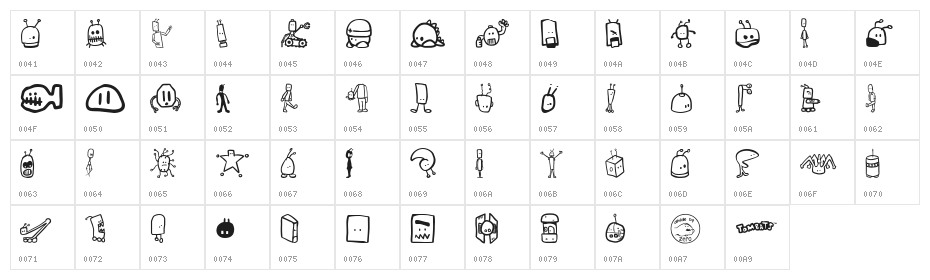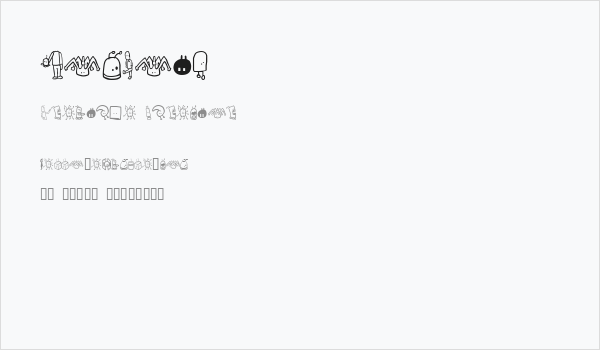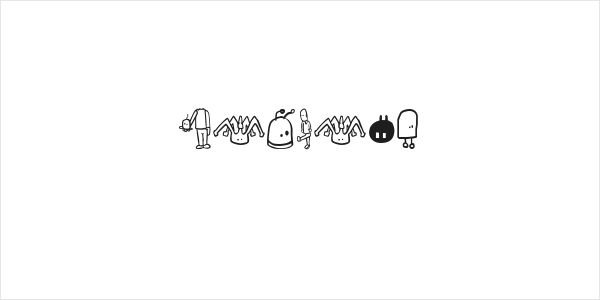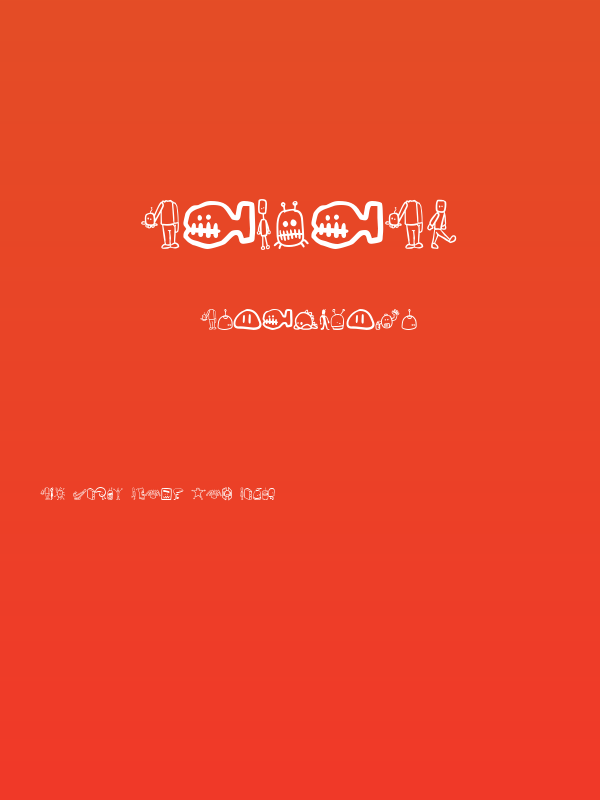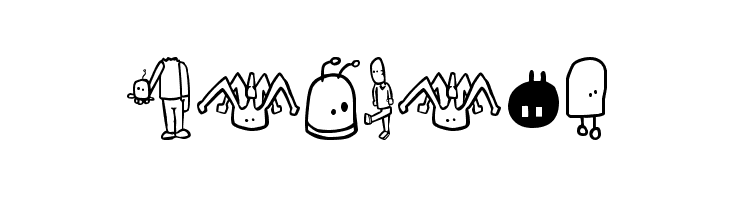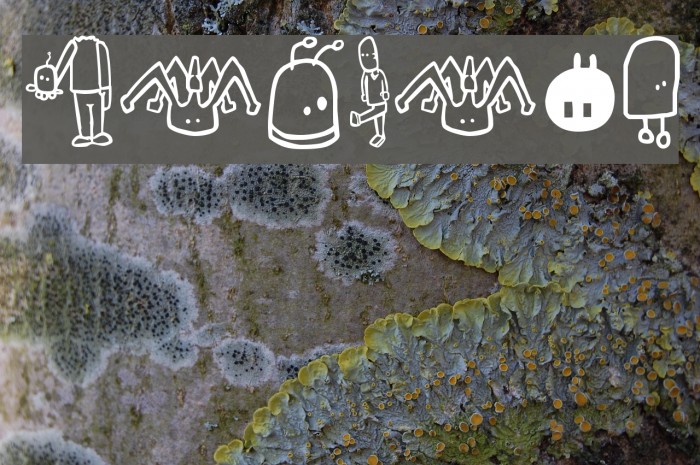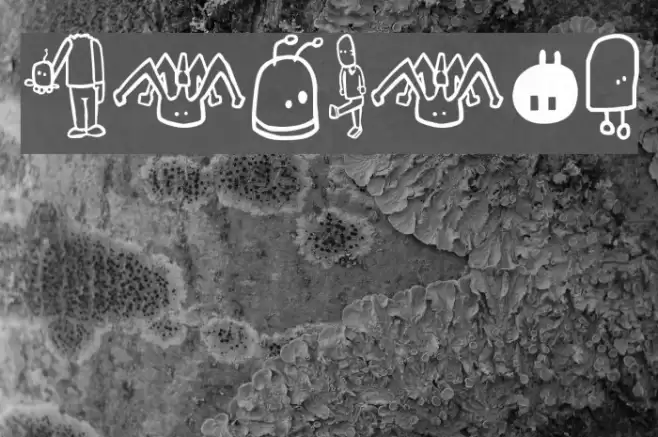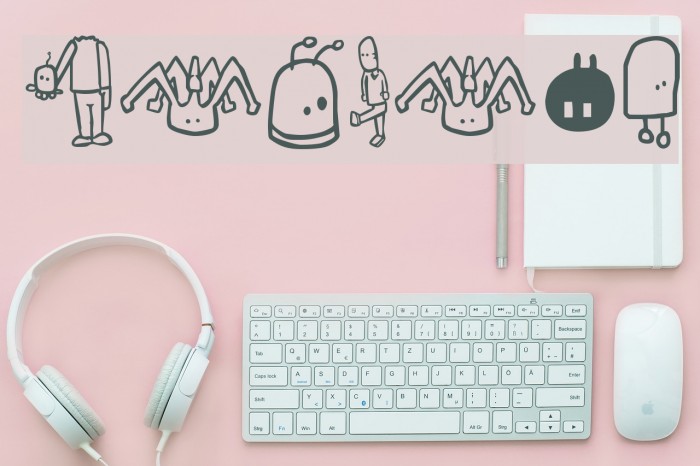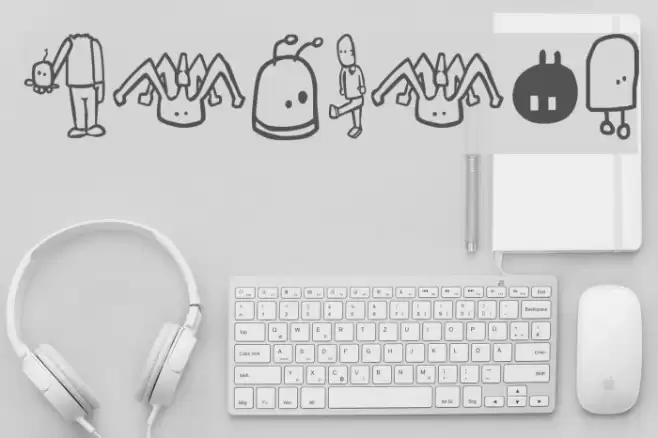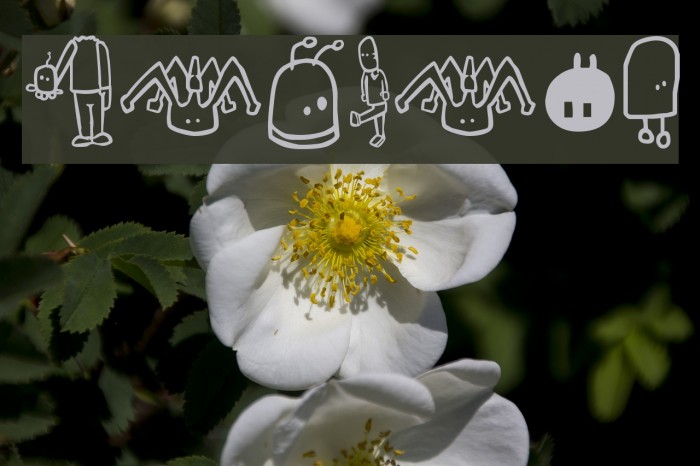
Tombots Font
| النمط العام | Playful, Artistic, Whimsical |
| حالة الاستخدام | Logos, Posters, Creative Projects |
| مشاريع مقترحة | Ideal for children's books, comic strips, playful branding, and creative posters. |